무료 폰트 다운로드 (상업적 이용 가능)
디자인 작업을 하거나 교육 자료를 만들 때, 상업적인 문서를 작성할 때, 저작권 문제 없이 사용할 수 있는 글꼴을 찾는 것은 매우 중요합니다. 오늘은 자유롭게 활용할 수 있는 '학교 안심 폰트'에 대해 소개해 드리겠습니다. 학교에서만 사용하는 것이 아니라 일반인도 사용이 가능합니다.
학교 안심 폰트란 무엇인가요?
학교 안심 폰트란 공공기관, 학교, 기업 등에서 추가적인 라이선스 문제 없이 무료로 사용 가능한 폰트를 의미합니다. 특히, 상업적 이용이 허용되는 폰트라면 교육자료, 강의 슬라이드, 공문서, 홍보물 등 다양한 곳에서 부담 없이 활용할 수 있습니다.
학교 안심 폰트를 선택해야 하는 이유
- 가독성이 우수함 - 공공기관에서 제공하는 폰트는 문서나 프레젠테이션 등에 최적화되어 있습니다.
- 다양한 스타일 제공 - 디자인 요소를 고려한 폰트들이 많아 교육자료 제작에도 적합합니다.
- 안정적인 지원 및 업데이트 - 지속적으로 관리되는 폰트들이 많아, 호환성 문제 없이 사용할 수 있습니다.
2025년 추천! 학교 안심 폰트 5가지
1. 학교안심 그림일기체
- 손글씨 느낌의 따뜻한 디자인으로 친근한 분위기를 제공합니다.
- 초등학교 교육자료, 동화책, 어린이용 콘텐츠에 적합합니다.
2. 학교안심 별자리체
- 개성 있는 스타일로 눈에 띄는 디자인이 가능합니다.
- 제목, 포스터, 이벤트 홍보물 제작에 활용하기 좋습니다.
3. 학교안심 알림장체
- 깔끔하고 정돈된 형태로 다양한 문서 작업에 적합합니다.
- 공문서, 안내문, 학습 자료 제작 등에 활용할 수 있습니다.
4. 학교안심 별빛하늘체
- 부드러운 곡선과 감성적인 느낌이 돋보이는 서체입니다.
- 감성적인 포스터, 인쇄물, 카드 뉴스 등에 적합합니다.
5. 학교안심 받아쓰기체
- 필기체 스타일로 정갈하고 자연스러운 글씨체를 제공합니다.
- 학습자료, 받아쓰기 교재, 노트 필기 등에 활용할 수 있습니다.
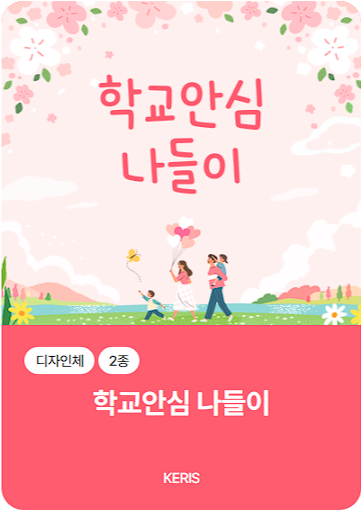
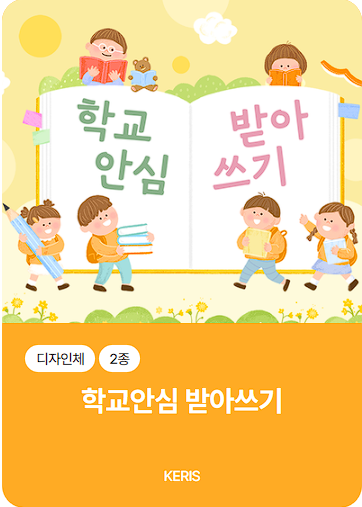
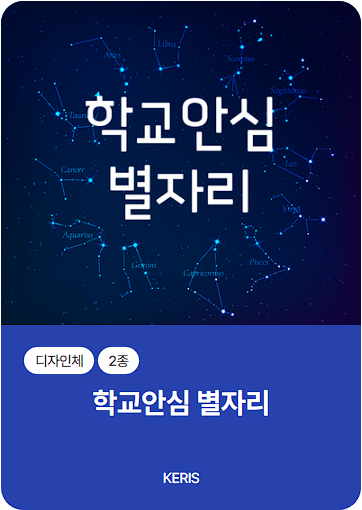
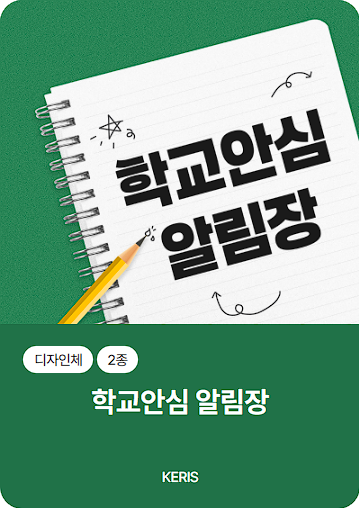
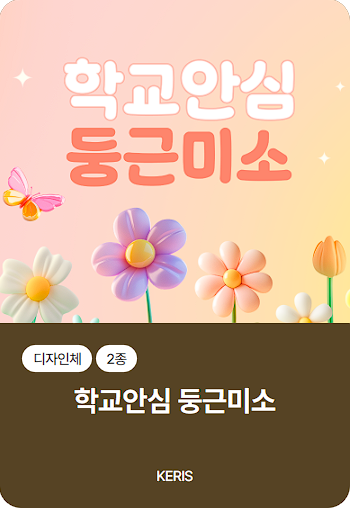
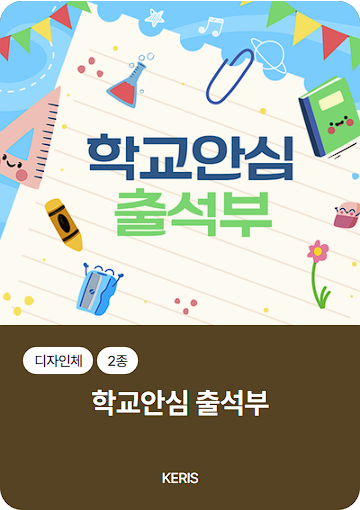
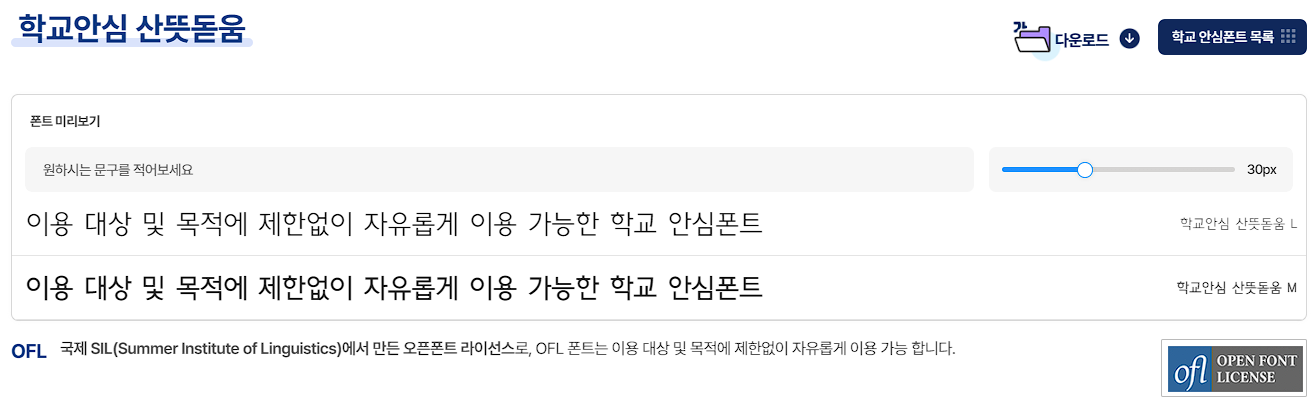
무료폰트 다운로드 추천 사용자
무료 폰트로 다운로드 가능하지만, 교육자료, 공문서, 홍보물, 프리렌서 등에 모두 활용이 가능하며 공공기관 뿐 아니라 영리를 목적으로 하거나 상업적으로도 사용이 가능합니다.
- 학교 과제 및 발표 자료에 사용할 무료 폰트가 필요한 학생
- 교육자료를 제작하는 선생님 및 교수님
- 공공 기관 및 학교 관련 디자인을 하는 프리렌서
- 각종 홍보물 제작 및 웹에 사용할 상업적 자료에 활용할 소상공인